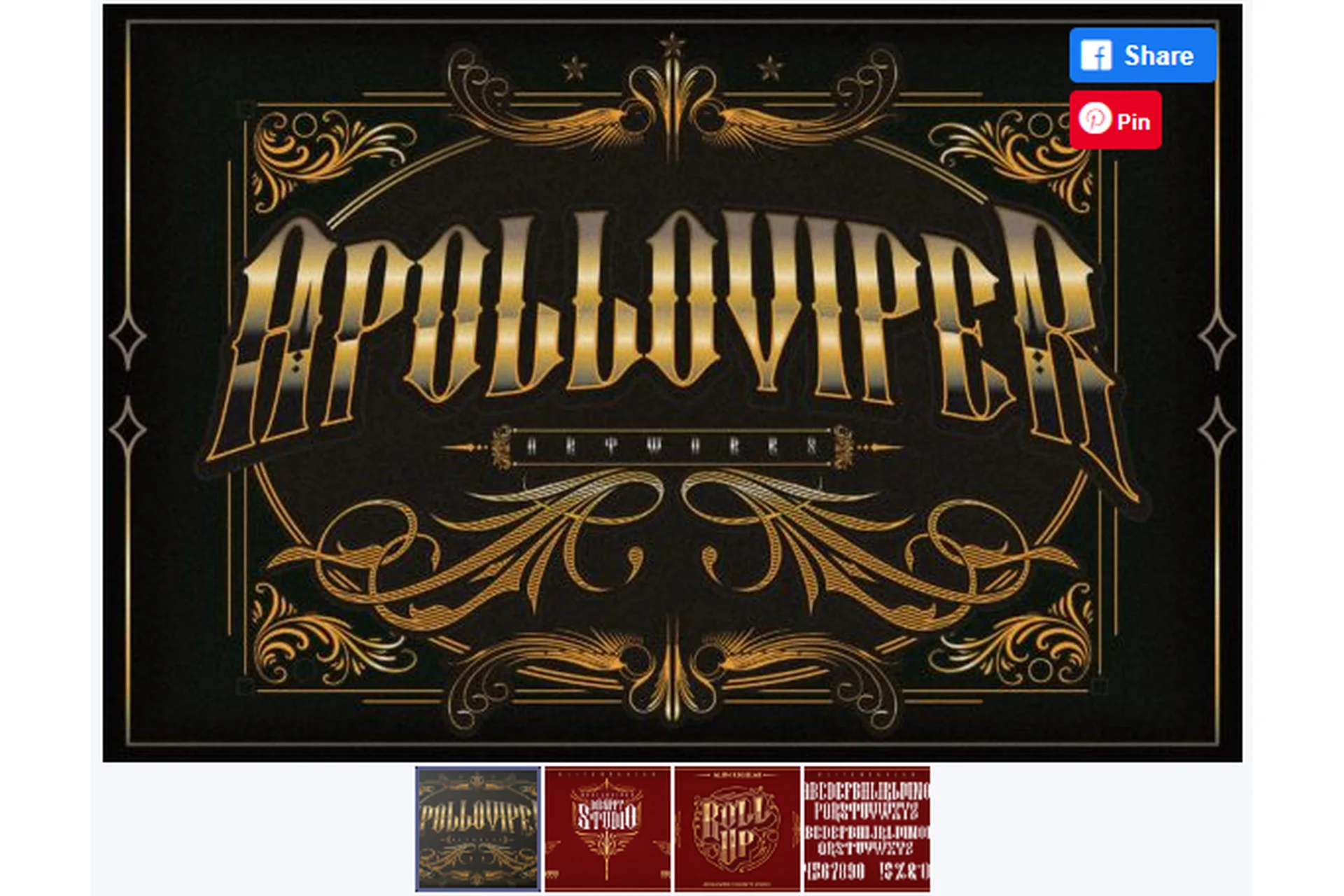
[Creativefabrica] Alifapolloviper Font (dignity.std) Артикул: 159983 В наличии 1950 ₽ 2100 ₽ Добавить в корзину Купить в один клик Почему такая цена? Категории: Шаблоны и темы, Creativefabrica, dignity.std Добавлено: 2022-01-08 Автор курса: dignity.std Цена у автора: 2100 руб. Сайт автора: Перейти Доступ: Облако Mail / Yandex / Google Загрузка: PC / Smartphone / Tablet Описание Отзывы Как получить курс? Почему такая цена? Alifapolloviper - красивый черный шрифт. Используйте этот шрифт для любого проекта, который требует индивидуального оформления! Отзывы (Читать все отзывы ->) Минимальная длина отзыва - 50 знаков. ИлиВойти Введите код с картинки: Отправить Я принимаю политику конфиденциальности С этим курсом также покупают 2010 ₽ 2700 ₽ [Creativemarket] Chlovia Шаблон презентации / Chlovia - Keynote Brand Guidelines (Elokka Std) В наличии Купить 2030 ₽ 445000 ₽ [Creativefabrica] All Fonts Collection - Mega Typeface Bundle (Maulana Creative) В наличии Купить 2030 ₽ 2400 ₽ [Creativefabrica] Inspace Font (NoahType) В наличии Купить 2020 ₽ [Creativefabrica] Alessandro Signature Font (Rissyletter Studio) В наличии Купить 1950 ₽ 5000 ₽ [Creativefabrica] Sannia Font (DisplayStudio_) В наличии Купить 2030 ₽ 2400 ₽ [Creativefabrica] Labella Font (NoahType) В наличии Купить Больше курсов из категории «Шаблоны и темы» 1950 ₽ 2500 ₽ [Creativefabrica] Mortend Font (Arterfak Project) В наличии Купить 1950 ₽ 2800 ₽ [Creativefabrica] Rooben Font (eafonts) В наличии Купить 2020 ₽ [Creativefabrica] Magical Storybook Toolbox for Procreate (Lysified) В наличии Купить 1750 ₽ [Creativefabrica] Bloomination Clipart (Tanya Kart) В наличии Купить 1950 ₽ 1960 ₽ [Creativefabrica] Gaston Font (Moove Studio) В наличии Купить 2020 ₽ [Creativefabrica] Alessandro Signature Font (Rissyletter Studio) В наличии Купить